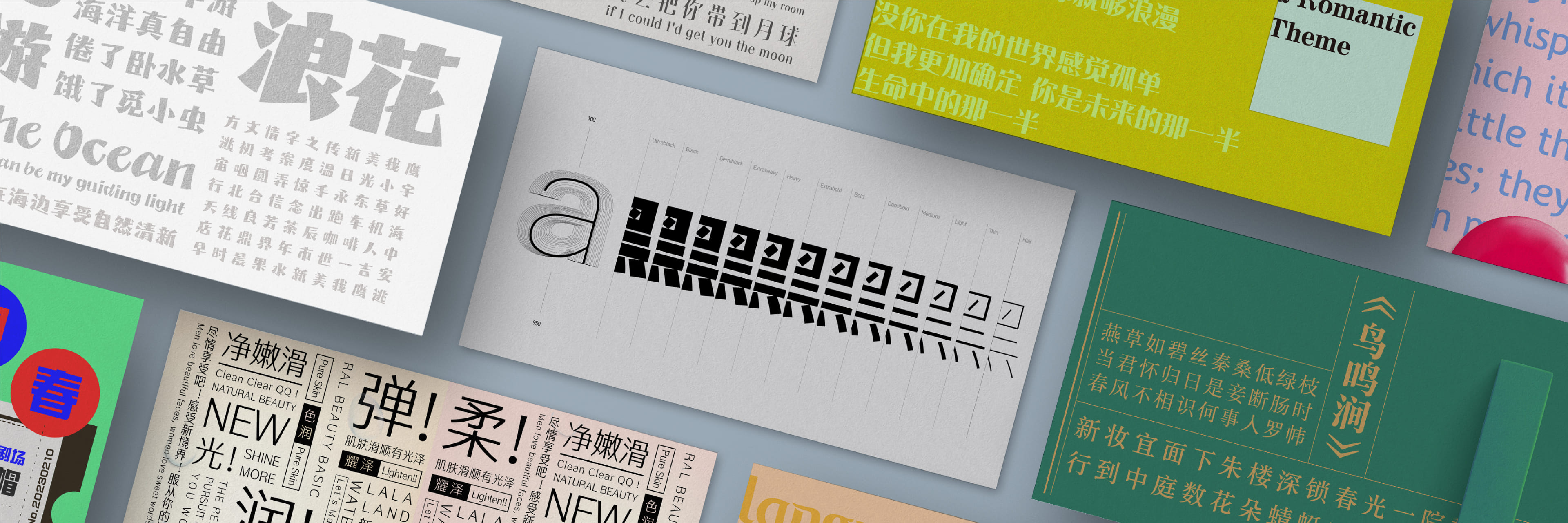
文鼎字型与设计师及书法家合作开发,使未来能有更多不同造型的字型产出,一同创造字型设计的丰富性。
可变式字型 Variable Fonts
可变式字型(Variable Fonts)是OpenType字体格式的一种,这种字型格式可支持字重(weight)、宽度(width)、倾斜(slant, italic)、光学尺寸视觉调整(Optical size)等可变属性的定义,用户在应用时可以立即变化出一套字体家族的不同样式。
可变式字型的特色在于可随使用者的设定或是依应用程序的自动判断,变化出将近无限种的字体属性组合。只需要一个字型档案,就可以无间段调整该字型提供的字重、字宽或对比等可变属性,让设计师用字的创意不再受局限,同时也减少了庞大字体家族所需要的海量存储器空间。